25 种你不知道自己需要的 Cricut 字体
已发表: 2023-02-04所以你认为你已经看到了 Cricut 切割机的所有最酷的字体? 再想一想。 这份出色的 Cricut 字体列表会让您想尽快开始下一个项目。 您所需要的只是一点设计灵感。
1.花束
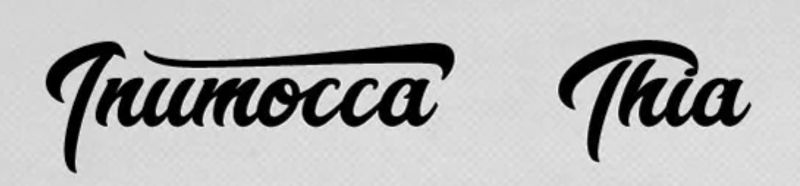
如果您正在寻找带有一点男子气概的女性魅力,请使用 Bouquet。 这是一种看起来清新现代的多功能脚本字体。 永远不要让 Bouquet 字体让你的 Cricut 设计项目看起来过时。
2.果冻豆
这是另一种有趣而轻松的脚本字体,您可以将其用于儿童设计或有趣的生日邀请。 Jelly Bean具有厚重的性质,笔触简单,整体看起来活泼。 使用这种风格会让你想起五颜六色的糖豆,你可以在看 rom-com 电影时咀嚼它。
3. 野榛子
如果您想将无衬线字体提升到一个新的水平,那么 Wild Hazelnut 字体是您的最佳选择。 这种风格让人想起纸上手写的文字,供您随意思考和涂鸦。 这种字体样式非常适合用于小型和大型 Cricut 设计项目。
4.比格迪
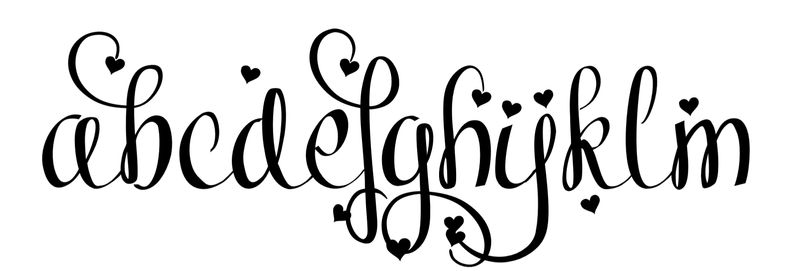
如果您正在为 Cricut 寻找装饰性的女性字体,Bigdey 是最佳选择之一。 精致的笔触与最后的小爱心完美融合。 但是,在较小的设计项目中使用它时要小心,因为它可能不太清晰。 偶尔使用此文本,具体取决于它在远处的可读性。
5.阿玛
Amagh 是 Cricut 设计的一种外观独特的字体,因为它粗壮的性质。 这种脚本字体样式具有更短和更重的笔划,具有更漂亮但更平易近人的吸引力。 这非常适合用于小型和大型设计,因为它比其他脚本字体更粗。
6. 苹果汁
对于所有古怪有趣的项目,请使用 Apple Juice。 这是一种现代类型的无衬线字体,具有看似孩子般的天性。 我可以想象图画书、着色书或任何适合儿童的漫画书上的这种字体样式。
7.布罗梅洛
Bromello 是一种优雅的字体,比此列表中的其他脚本字体略重。 使用这种风格的优势是你可以将它用于更小和更大的项目。 笔画和字母具有完美的字距调整,在任何媒体上都清晰可辨。
8. 草莓花
Strawberry Blossom 拥有令人惊艳的花饰,在任何媒介上都不会过于突出。 这种字体对你的 Cricut 设计的永恒吸引力也看起来优雅和少女。 如果您经营珠宝系列或化妆品公司,请使用 Strawberry Blossom 作为您的品牌和营销材料。
9. 复古派对
如果你想要一点经典的优雅,这是一种很好的字体。 我可以在夫妻餐厅的社交媒体帖子或西式酒吧的营销材料上看到这种字体样式。 粗笔画使这种风格对于广告牌、海报或传单等离线项目更清晰。 然而,这对于社交媒体帖子、横幅广告或登陆页面等在线项目也非常有用。
10.阿瓦林
Avaline 拥有纤细的笔触,非常适合女性服装品牌或任何有女性受众的项目。 虽然这是一种脚本字体,但字母之间的字距非常好,即使在更大的离线和在线设计项目中也能完美使用。 最后,笔触尖端的漂亮圆点和泪滴形元素使这种风格更具吸引力。
11.萨克拉门托
Cricut 的衬线字体看起来经典而专业,非常适合具有更正式品牌或目的的品牌和项目。 Sacramento 字体是一种独特的衬线字体,适用于您的金融或教育网站、应用程序和广告设计。
12. 扭曲
Retwisted 字体风格让我想起了 Tiki 酒吧或充满气球和三角旗的有趣狂欢节派对。 这种字体风格充满乐趣和乐趣。 但是,请确保偶尔使用此字体样式,因为它可能不适用于所有类型的设计项目。 例如,将此字体用作标题或副标题,但切勿将其用于长文案。
13. 兴萨
这种厚重的字体风格看起来友好而独特,但又有趣又热情。 Hinsa 字体可以成为社交媒体帖子或着陆页标题的醒目标题。 此外,Hinsa 还可以用于更大的线下材料,因为大胆的风格可以从远处看到。
14. 停电日出
Blackout Sunrise 是一个独特的平板文本,在深色背景中可能会很好。 独特的字体在线条内看起来似乎是透明的,正是这种字体令人着迷的原因。 使用此字体作为海报或传单的标题,并搭配简单的无衬线字体作为副本,一切顺利!
15. 黑色法庭
Black Chancery 字体具有哥特式魅力。 它也比此列表中的其他字体样式更正式一些。 如果您想要更异想天开但散发出大男子主义气息的东西,那么 Black Chancery 是完美的选择。
16.马布尔桑
这是一款非常花哨、有品位的无衬线字体,外观非常别致。 其纤细和垂直的方向使其时尚而优雅,适合具有更严肃目的的 Cricut 设计。 看着这个字体让我想起了老电影、剧院和红地毯。
17. Adlery Pro
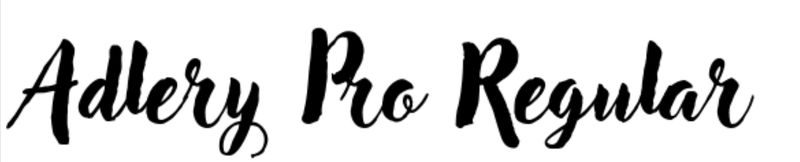
Adlery Pro 是一种程式化的脚本字体,与此列表中 Cricut 的其他脚本字体不同。 线条或字母中的瑕疵赋予它粗犷而温馨的触感。 这是一种适用于网站、应用程序、社交媒体页面以及印刷材料的好字体。
18.桑塔纳
如果您会立即从 Santana 字体中注意到一件事,那就是每个字母之间精致的字体字距调整。 这些字母彼此之间的间距完美,由于其易读性,即使在更大的设计上也使该字体非常出色。 简洁的线条和微妙的曲线也使它保持轻盈和专业。
19.八一
八一是另一种独特的字体,具有强烈的吸引力。 每个字母的笔画都细而圆滑。 字母也更宽,更具圆形吸引力,使整体看起来在视觉上更有趣。 将其用于您的标题或最小副本,并将其与另一种类似的现代字体配对以获取更长的文本。
20.外星人和奶牛
我完全可以在一家西式运动酒吧的招牌上看到字体 Aliens and Cow。 它具有简单而经典的外观,适合 Cricut 老式设计。 但是,您仍然可以在社交媒体帖子、电子邮件通讯标题或名片中使用这种字体样式。